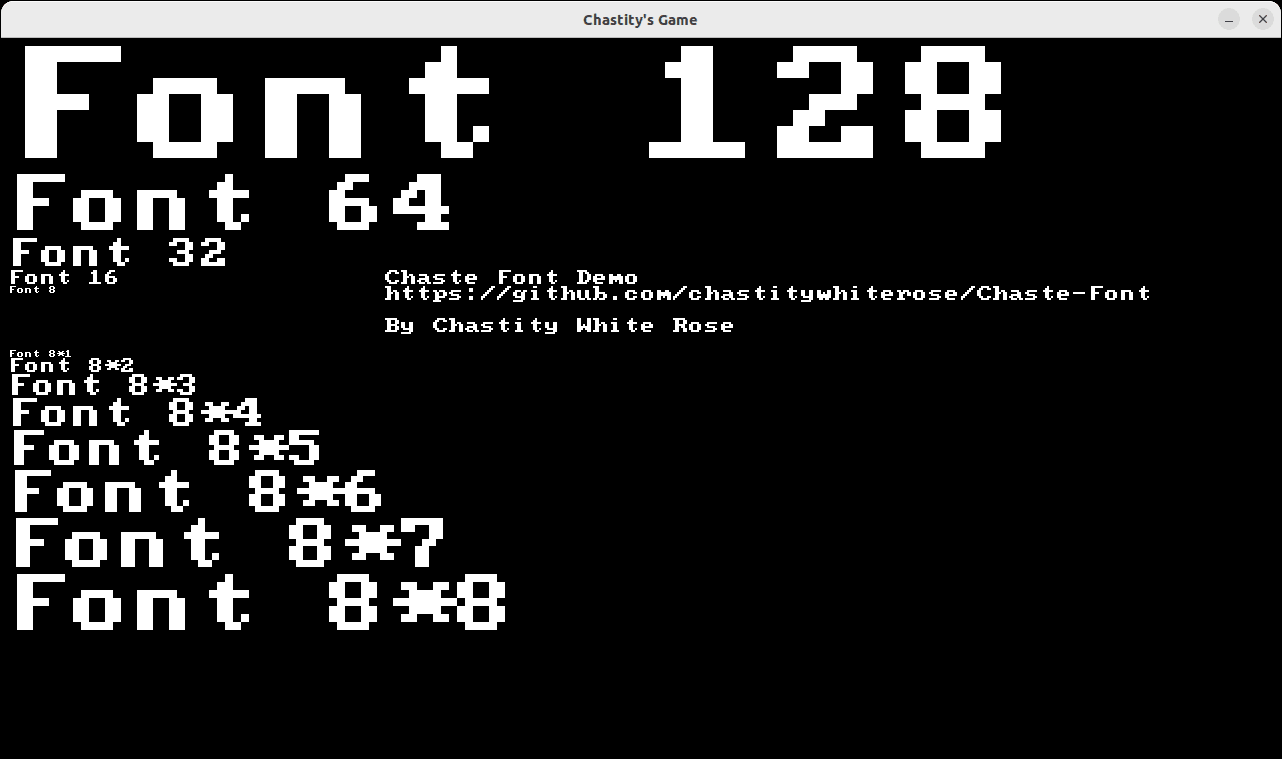
Бесплатный шрифт «Chaste Tris Bitmap Fonts»
На восприятие игры влияет не только графика и музыка, но и подача текстовых сообщений, для чего стоит подбирать подходящий шрифт. Например, товарищем Chastitywhiterose на днях был сделан и выложен новый шрифт «Chaste Font», чтобы использовать его в играх ретро-стиля. Использовалась структура Raylib texture2D и файлы изображений всех печатных символов ASCII.